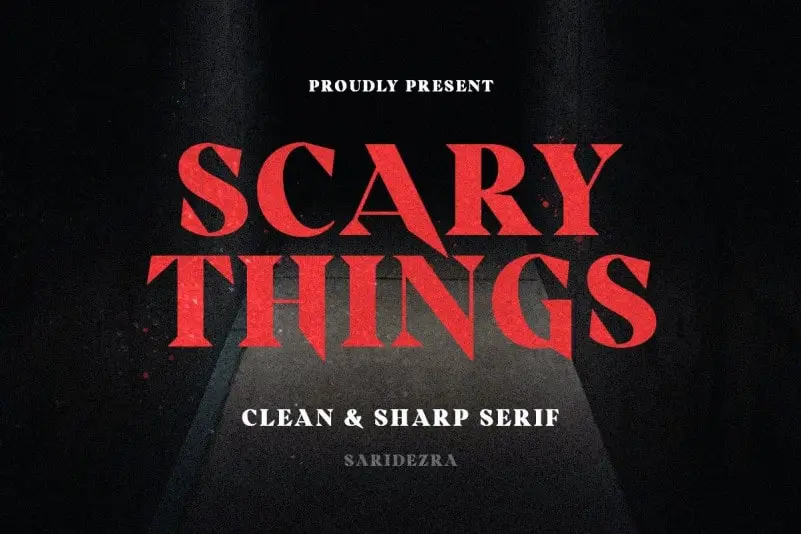
Scary Things Serif Font
A fonte ‘Scary Things Serif Font’ é uma tipografia serif geometrica inspirada na impressão a leme, desenvolvida por Sarid Ezra para 99designs. Ela tem uma aparência clara e aguçada, que lhe confere um toque perturbador e assustador. Este tipo de letra é ideal para poster filmes de terror e horror, tornando seu design imediatamente chamativo. Suas formas únicas e afiadas garantem que o seu trabalho de arte esteja em destaque em qualquer situação. A fonte também é versátil o suficiente para ser usada em diversos projetos gráficos, sem perder sua qualidade. Além disso, ela suporta múltiplas línguas, permitindo-lhe expressar suas ideias em diferentes idiomas. Portanto, estou pronto para transformar seus próximos cartazes de Halloween com esta fonte!